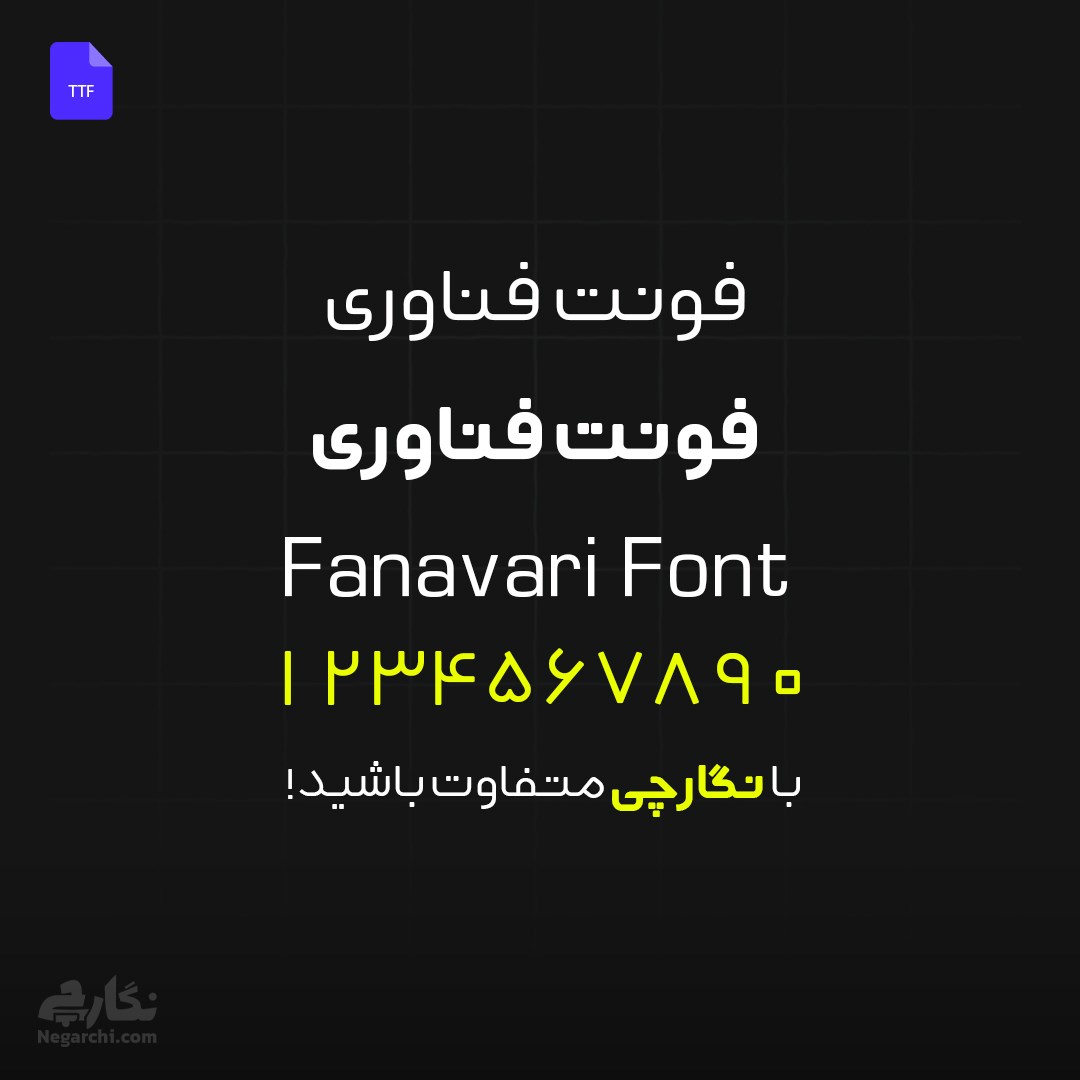
فونت فارسی فناوری (Fanavari) یک فونت هندسی مناسب عنوان و متن است که توسط مرحوم استاد مسعود سپهر در سال ۱۳۹۹ طراحی شده است. این فونت رایگان در دو وزن Regular و Bold و با فرمت TTF ارائه میشود و برای استفاده در پروژههای گرافیکی و طراحی فارسی گزینهای کاربردی محسوب میشود.
فونت فارسی فناوری (Fanavari) از مجموعه فونتهای آزاد و کاربردی فارسی است که با ساختاری هندسی برای استفاده در عنوانها و متن طراحی شده است. این فونت توسط مرحوم استاد مسعود سپهر در سال ۱۳۹۹ طراحی و منتشر شده و به دلیل ساختار خوانا و طراحی ساده، در پروژههای مختلف گرافیکی و دیجیتال قابل استفاده است.
فونت فناوری به صورت رایگان ارائه شده و کاربران میتوانند آن را در پروژههای طراحی، وب و محتوای دیجیتال استفاده کنند. ساختار هندسی این فونت باعث شده در تیترها و متنهای کوتاه جلوهای منظم و حرفهای ایجاد کند.
فونت فناوری با فرمت TTF ارائه شده و دارای دو وزن اصلی است که برای استفاده در عنوانها و متنهای مختلف کاربرد دارد. این ساختار ساده باعث میشود کاربران بتوانند به راحتی از آن در نرمافزارهای مختلف طراحی و تایپوگرافی استفاده کنند.
فونت فناوری Fanavari یک فونت فارسی با ساختار هندسی است که برای استفاده در عنوانها و متنهای کوتاه طراحی شده است. طراحی این فونت توسط مرحوم استاد مسعود سپهر در سال ۱۳۹۹ انجام شده و به دلیل ساختار ساده، خوانا و منظم در بسیاری از پروژههای گرافیکی کاربرد دارد. این فونت در دو وزن Regular و Bold ارائه شده و فرمت TTF آن باعث میشود در اکثر نرمافزارهای طراحی و سیستمعاملها قابل استفاده باشد. ظاهر متعادل و مدرن آن باعث میشود در طراحی پوستر، بنر و محتوای دیجیتال جلوه مناسبی ایجاد کند.
فونت فناوری Fanavari در دو وزن اصلی طراحی و منتشر شده است. این دو وزن شامل Regular برای استفاده در متنهای معمولی و Bold برای عنوانها و تیترهای برجسته هستند. وجود این دو وزن باعث میشود طراحان بتوانند در پروژههای مختلف ترکیب مناسبی از تایپوگرافی ایجاد کنند. به طور معمول از وزن Bold برای جلب توجه در تیترها و از وزن Regular برای متنهای کوتاه یا بخشهای توضیحی استفاده میشود.